2026年9月20日,“字美中华——中华精品字库工程公益应用计划”四期发布会在北京北大科技园创新中心举行。发布会由北京大学中国文字字体设计与研究中心(以下简称“字体中心”)、北京北大方正电子有限公司(以下简称“方正电子”)、中国书法出版传媒有限责任公司联合主办,北京大学王选计算机研究所、广州国家版本馆、中国中文信息学会汉字字形信息专业委员会、新方正控股发展有限责任公司(以下简称“新方正集团”)、北京北大科技园有限公司合作支持。
会上发布毛公鼎金文、石鼓文篆书、秦简、秦小篆、虞世南楷书、颜真卿行书等14款最新书法字库。至此,中华精品字库工程累计发布精品字库达到61款,全部纳入“字美中华”公益应用计划,继续免费向公益组织、新闻出版单位、政府机构、学校、博物馆、个人提供5年使用授权,并覆盖大型会展、体育赛事应用场景。活动现场,“学习强国”学习平台、中国精神文明网网站、新华社新媒体中心、北京日报社、北京大学、广东省出版集团有限公司、人民文学出版社、清华大学艺术博物馆、深圳壹基金公益基金会等用户代表,接受主办方颁发的字库授权证书,四期公益应用计划正式启动。
多方寄语精品字库发展
凝聚书法文化传承发展合力
发布会上,北京大学副校长朴世龙,方正电子总裁张建国,全国政协委员、中国书法家协会副主席张继,教育部语言文字信息管理司标准处处长李强先后致辞,从产业实践、学术支撑、艺术把关与语言文字事业发展等角度寄语工程。
朴世龙副校长在致辞中回顾了汉字信息化的历程,从王选教授主持研制汉字激光照排系统、让中文真正走进计算机世界,引领我国印刷出版行业实现“告别铅与火、迎来光与电”的历史性变革,到2005年教育部语言文字信息管理司与北京大学共建中国文字字体设计与研究中心。二十余年来,字体中心始终致力于用技术守护汉字之美,取得了一系列成果,中华精品字库工程是其中最具代表性的。他表示,北京大学是中国人文学术研究的重镇,也是汉字技术创新的高地,将在教育部语言文字信息管理司的指导下,一如既往地支持中心建设发展,推动更多书法经典从馆阁走向大众、从学术走向应用。
张建国总裁在致辞中表示,九年来,中华精品字库工程历经四期发布,累计推出61款精品字库,已在国家语言资源服务平台和方正字库官网上线,后续更重要的是“推广与深度应用”, 61款精品字库全部纳入公益应用计划,继续向公益组织、新闻出版单位、政府机构、学校、博物馆和个人免费开放字体使用授权。方正电子将联合各方,拓展应用场景,让社会大众在日常生活中,时时处处浸染书法之美、汉字之美,让“中国人,方正字”的愿景走进现实。
张继副主席在致辞中表示,书法是以汉字为载体的书写艺术,融入了中华优秀传统文化所蕴含的思想观念、价值标准、人文精神和道德规范,成为共同的精神标志。“中华精品字库工程”精选历代书法名家的代表作品开发成电脑字库,中国书法家协会负责开发字体的遴选和质量审核,帮助推荐书法家创写字稿、组织专家评审把关。这一造福千秋万代的文化工程,将深藏于博物馆的经典转换成敲击键盘即可调用的61款字库,让上下几千年前的笔墨得以时时亲近、代代相传。衷心希望社会各界积极参与“字美中华”公益应用计划,使用才是最好的传承,在使用中感受中国书法的魅力,坚定文化自信,弘扬中华优秀传统文化。
李强处长在致辞中表示,2022年10月,习近平总书记考察河南殷墟遗址时强调,“中国的汉文字非常了不起,中华民族的形成和发展,离不开汉文字的维系”。当前,生成式人工智能正深刻重塑语言文字的应用场景与传播方式。2025年,教育部、国家语委、中央网信办联合印发《关于加强数字中文建设,推进语言文字信息化发展的意见》, 61款精品字库开发完成,字体智能生成等关键技术取得突破,都为数字中文建设提供了坚实资源与技术支撑。教育部语言文字信息管理司将一如既往地支持北京大学字体中心和工程建设,进一步加强中华精品字库的推广,以文字之美活化应用,为教育强国、科技强国、文化强国建设贡献更大力量。
中华精品字库工程四期成果发布
毛公鼎金文等14款最新书法字库隆重亮相
书法是以汉字为载体的书写艺术,是中华文化的璀璨瑰宝。为传承发扬书法文化,推进书法经典跨越时空传承,2017年,方正电子申请立项并获国家批准,正式启动“中华精品字库工程”。工程是中华优秀传统文化传承发展工程支持项目,由中国文学艺术界联合会、国家语言文字工作委员会共同指导,精选中国历代书法名家代表作品开发成电脑字库,中国书法家协会负责开发字体的遴选和质量审核,北京大学中国文字字体设计与研究中心与方正电子负责字库开发。
发布会上,中华精品字库工程设计总监、方正字库设计总监汪文介绍了中华精品字库工程的发展历程,发布了工程最新字体成果——毛公鼎金文、石鼓文篆书、秦简、秦小篆、钟繇小楷、始平公造像楷书、张黑女楷书、董美人楷书、虞世南楷书、颜真卿行书、祝允明小楷、邓石如篆书、何绍基行书、吴昌硕篆书共14款,并对各款字体的风格特征作了详细说明。
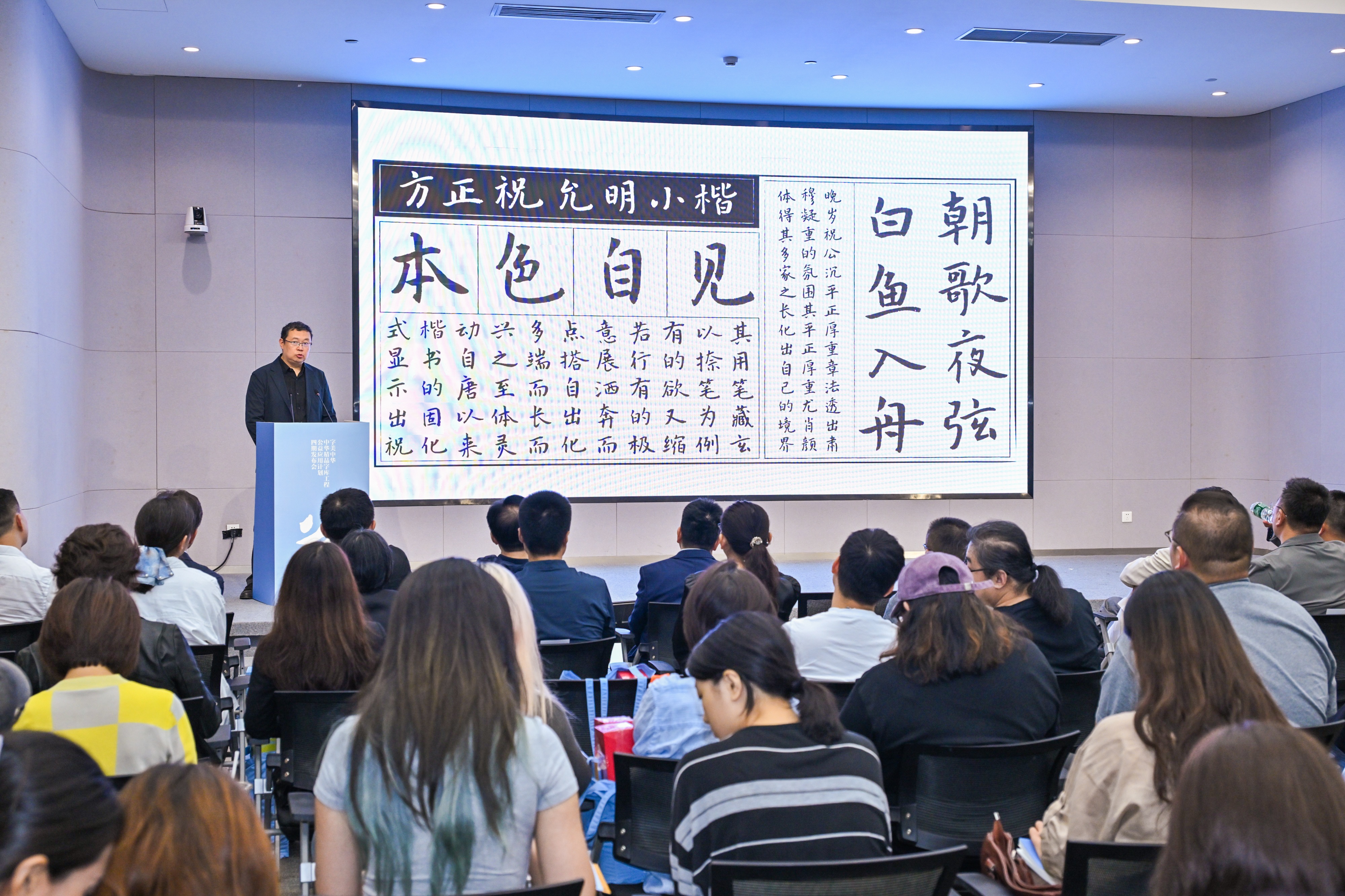
本期发布的14款字库,在书体源流上尤具深意:上溯商周毛公鼎金文、先秦石鼓文,中经秦简牍与秦小篆“书同文”的统一气象,下接钟繇小楷的楷法滥觞、北朝造像与隋人墓志的方严精整,再到初唐虞世南的冲和博雅、颜真卿行书的沉雄勃发,直至祝允明、邓石如、何绍基、吴昌硕的文人翰墨,贯通了汉字书体演变的完整链条。至此,工程累计发布61款精品字库,将商周金文、先秦石鼓、秦篆简牍、魏碑唐楷直至明清文人书法的演变长卷,完整呈现在数字世界之中。
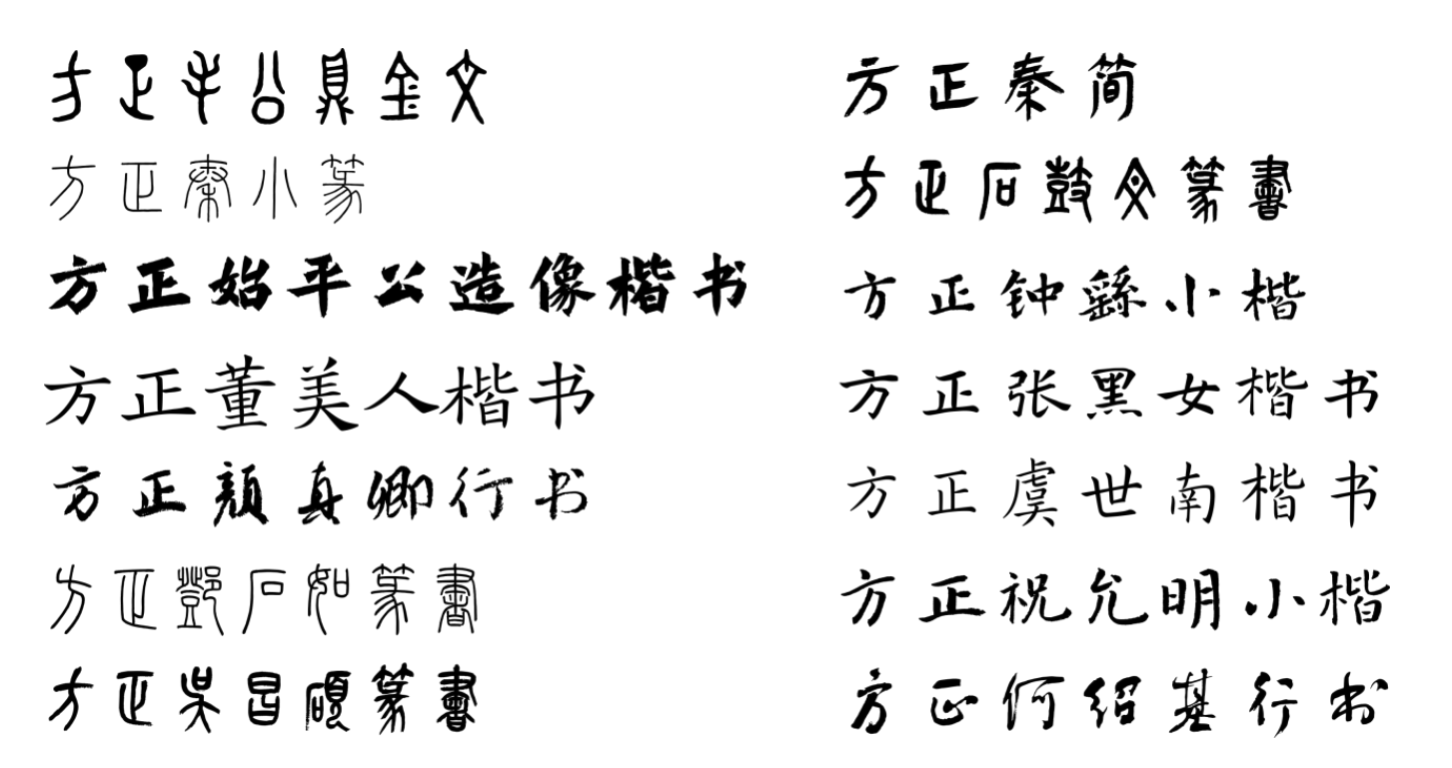
中华精品字库工程14款最新字体成果列表
其中,毛公鼎为西周晚期青铜重器,铭文近五百字,是已知铭文最长的青铜器;石鼓文被后世誉为“石刻之祖”。开发过程中,项目团队以历代著录与馆藏拓本为字型蓝本,组织文字学专家对古文字字形逐字考释,对残损缺佚文字依据书风补创,将深藏于博物馆、著录于金石之学的经典,转化为敲击键盘即可调用的字库,让三千年前的笔墨与今天的屏幕相遇,成为书法经典“活起来”的时代注脚。
方正毛公鼎金文字体样张展示
方正虞世南楷书字体样张展示
发布会上,“学习强国”学习平台、中国精神文明网网站、新华社新媒体中心、北京日报社、北京大学、广东省出版集团有限公司、人民文学出版社、清华大学艺术博物馆、深圳壹基金公益基金会等单位的用户代表上台,接受主办方颁发的字库授权证书。通过公益授权,工程字体将进入更多机构的日常应用场景,促进社会各界更广泛地了解和认知中华精品字库,带动更多人在工作、学习和生活中把经典字体用起来。
同时,会上举行“字美中华——中华精品字库工程公益应用计划”四期启动仪式,全国政协委员、中国书法家协会副主席张继,教育部语言文字信息管理司标准处处长李强,中国平安集团品牌宣传部总经理、党委宣传部部长陈遥,中国书法出版传媒有限责任公司副总经理张百军,北京大学王选计算机研究所副所长邹磊,广州国家版本馆副馆长黄磊,新方正集团党委副书记施华,北京北大方正电子有限公司CEO郑伟共同上台,正式启动四期计划。四期计划的启动,标志着中华精品字库工程进入字体成果进一步扩容、公益应用不断深化的新阶段:61款精品字库将在公益授权的带动下,覆盖更多应用场景,让书法经典在出版、教育、办公、设计等领域更多使用。
“字美中华——中华精品字库工程公益应用计划”四期启动仪式
嘉宾对谈聚焦书法字体开发应用
多领域视角畅谈汉字文化传承未来
随后的嘉宾对谈环节,中国人民大学艺术学院教授郑晓华,艺术与设计杂志社社长、总编辑钱竹,深圳市平面设计协会主席刘钊,人民文学出版社首席编辑刘静,方正字库设计总监汪文,以书法经典的“新生”与“走进时代”为主题,围绕中华精品字库工程的意义,书法经典在高校教学、出版、设计各领域的应用实践等话题展开交流。各位嘉宾深入浅出的见解,为当下中华优秀传统文化特别是书法文化的传承发展带来诸多启发。
精品字库展陈呈现汉字之美
商周至明清书体演变长卷一览无余
发布会同期特设中华精品字库展陈区,集中陈列工程61款字体样张合集,并展示以精品字体为设计元素的书籍、卷轴、帆布袋、台灯、雨伞、啤酒等实际商品和文创产品,以直观可感的方式呈现工程阶段性成果,让书法艺术以更鲜活的形态走进大众生活。
让书法经典融入大众生活
助力中华优秀传统文化传承发展
“字美中华——中华精品字库工程公益应用计划”四期发布会的举办,一方面通过61款精品字库成果的集中展示,向大众传递汉字之美,提供更丰富的优质字体选择;另一方面以科技与文化融合的成果赋能社会公益,通过为公益事业提供正版字体支持,提升大众视觉美感,赋予其文化的温度与内涵。
随着“字美中华”公益应用计划的不断深入推广,将有更多单位与个人使用中华精品字库,让普通民众在日常工作、学习和生活中,时时、处处领略书法之美、汉字之美,在使用中感受中国书法艺术的魅力,感受中国书法背后中国人的价值标准、人文精神,从“字载中华”到“字美中华”。